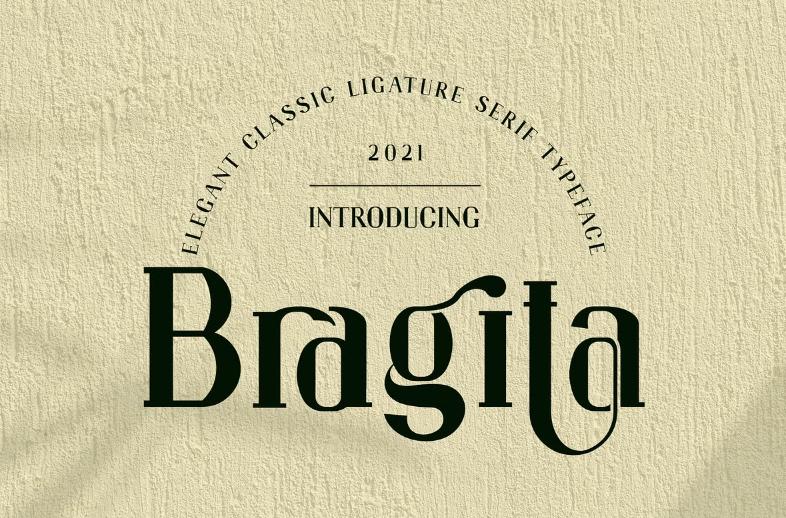
[Creativefabrica] Bragita Fuente Font (humaira_std)
Bragita - это элегантный и современный шрифт с засечками. Он одновременно современный и ностальгический и отлично подходит для логотипов, журналов и постов в социальных сетях. Для тех из вас, кто нуждается в стильном, стильном и шикарном штрихе к своим дизайнам, этот шрифт создан специально для вас!